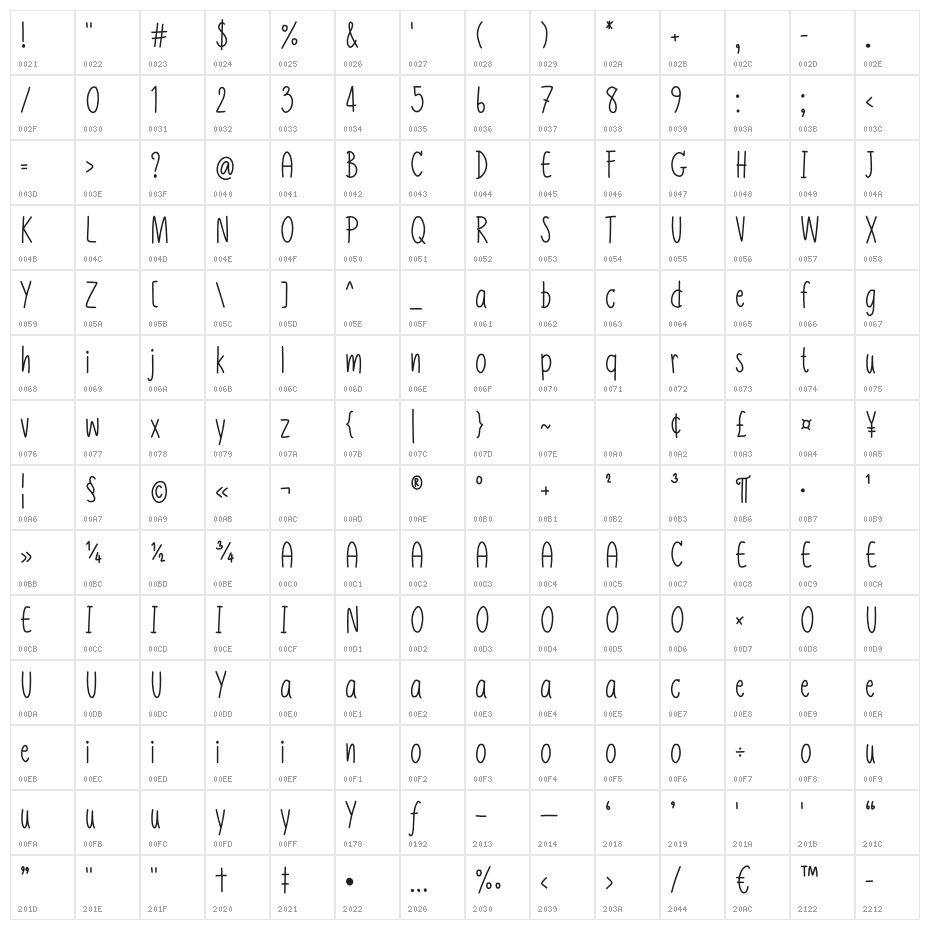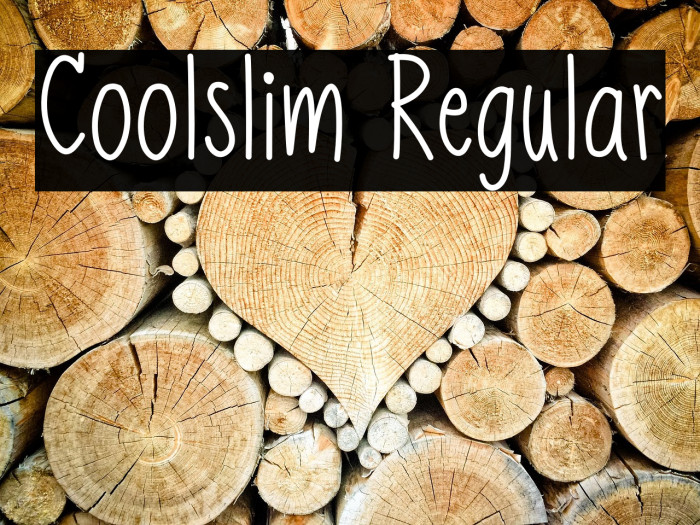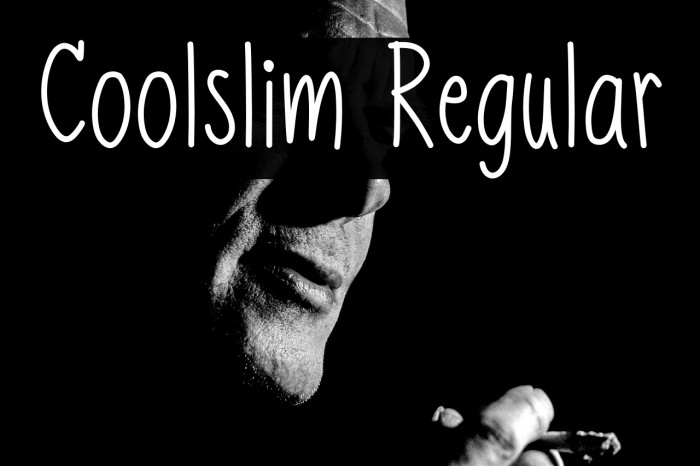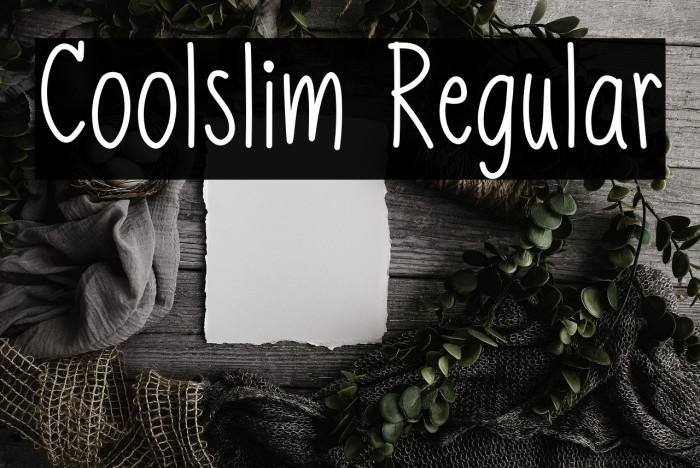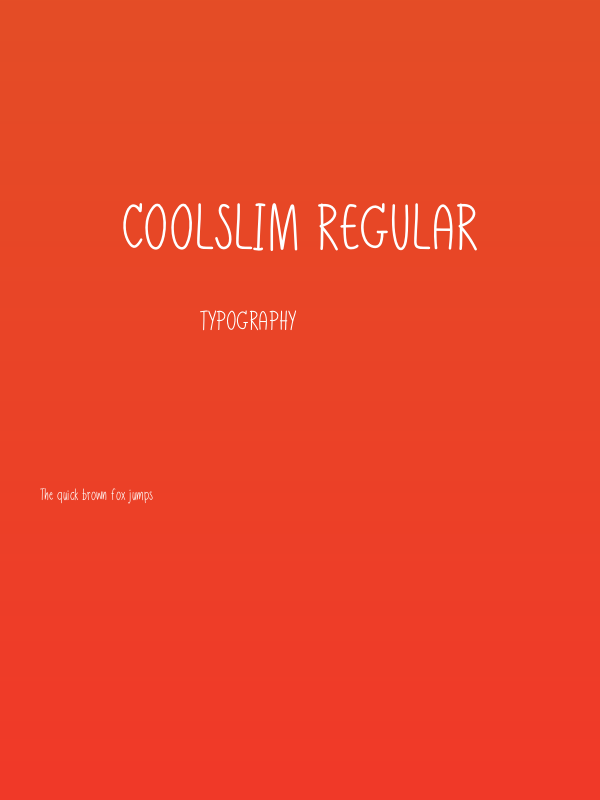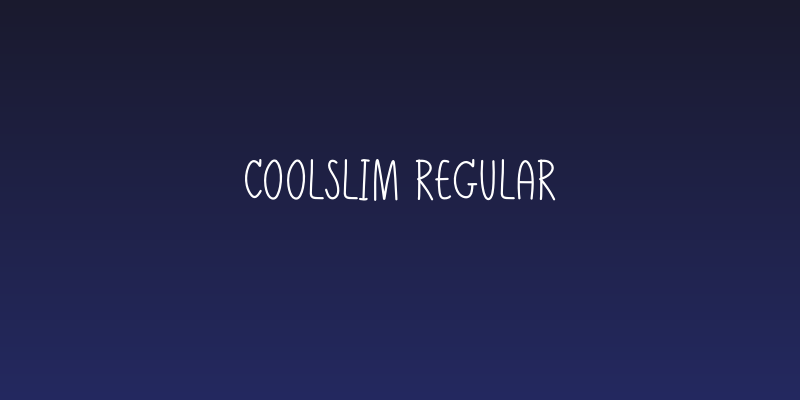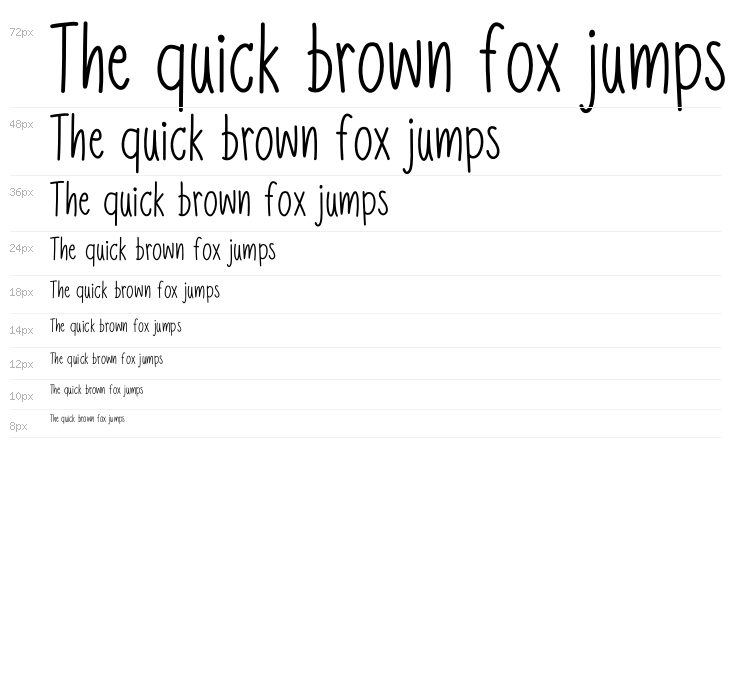
Coolslim Regular Font
| Stile generale | Casual |
| Caso d'uso | Headlines, Informal text, Branding |
| Progetti proposti | Ideal for children's books, greeting cards, casual branding, and social media graphics. |